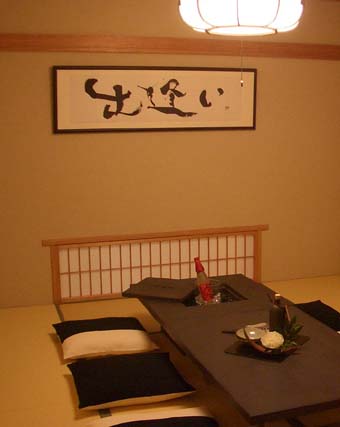
2005年4月末に新規オープンとなった住宅展示場の和室に 飾って頂いています。お客様との出会いを大切にしたいという、久保さまをはじめスタッフの皆様の思いがこめられた書です。私にとっても素晴らしい出会いとなりました。
横に長いので、ひずみが起こらないよう、 アルミ素材のフレームを使用。表面はリアルな木目調です。
関から入ってすぐ横にある和室は、この展示場の見せ場です。 そこに合う書道を・・・ということで、色々探してたどり着いた文字屋のHP。 運命の出逢いは間違っていなかったと、私も含め関係者一同感じております。想像以上のすばらしい作品に一同感激しています。
落ち着いた和室の中にダイナミックな額がとても似合い、
内覧会を行った際にも、とても好評でした。